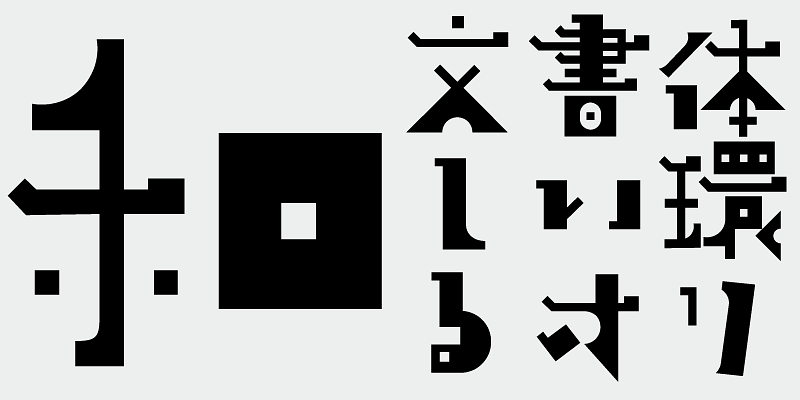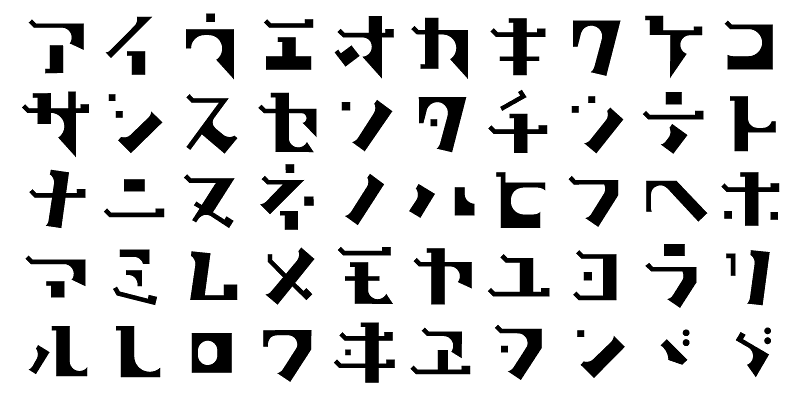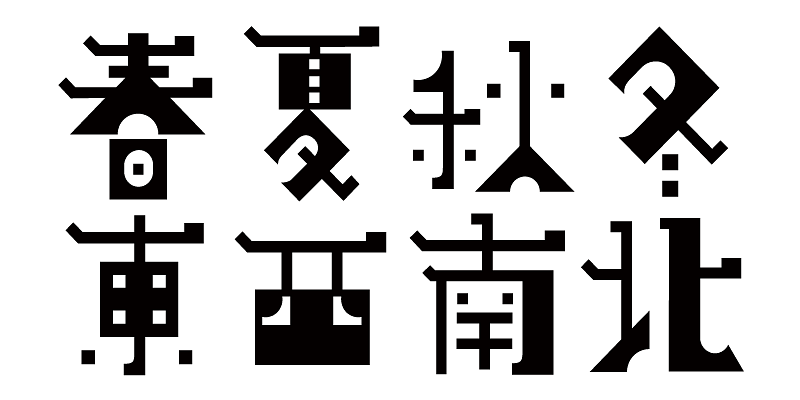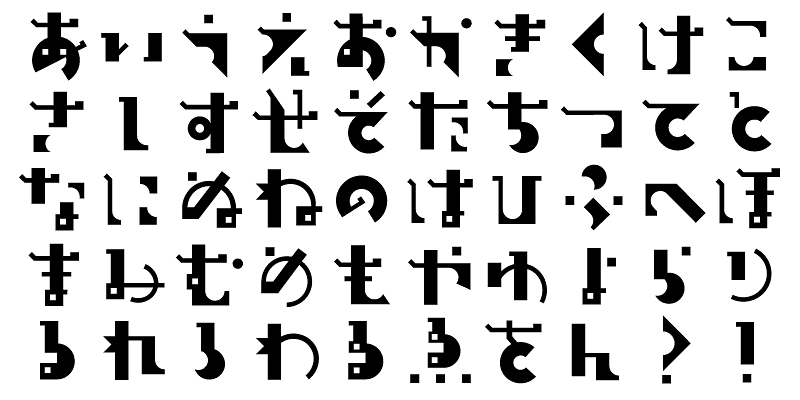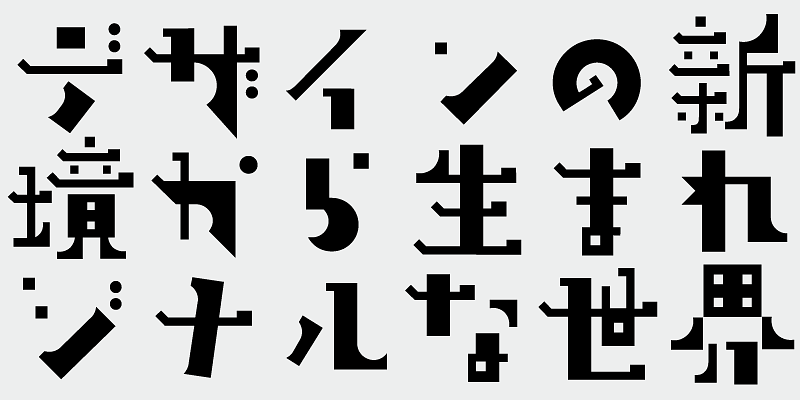
서체는 가독성도 중요하지만, 제 경우에는 제작 시 문자뿐만 아니라 그림과 기호로도 나타나 시각적으로도 즐거움을 주는 큰 도전을 했습니다. 이는 훗날 디자인된 AB-Shoutenmaru 서체의 큰형님뻘이 됩니다.
이 글꼴에는 신문사, 출판사, 언어 연구소가 만든 문자 빈도표에서 선정된 가장 많이 사용되는 간지 문자 1,000개와 더불어 206개의 가나 문자와 구두점이 포함되어 있습니다.
오늘날 일본어 글꼴 제작에서는 JIS 표준의 7,000자가 필수로 간주됩니다. 그러나 모든 글꼴에 정말 7,000자가 필요할까요? 사진 식자 시대에는 훨씬 적은 수의 문자가 필요했습니다. 독립 서체 디자이너 그룹인 FONT1000은 그 간단한 질문으로 시작했습니다. 일본어 서체에 필요한 최소 1,000자의 한자(표의 문자)를 선택했고 이를 지원하는 서체와 글꼴을 적극적으로 만들었습니다. 이 1,000자의 한자 문자 세트는 신문사, 출판사, 언어 연구 기관 등에서 수집한 문자 빈도 데이터를 사용하여 선택되었으며 가나 음절 문자 및 구두점도 포함합니다. FONT1000은 2001년에 25명의 디자이너와 25개의 서체로 시작했습니다. 현재는 130개의 서체를 보유 중이고 거의 40명의 멤버를 포함하도록 성장했으며, 더 많은 문자가 있는 글꼴 작업이 가능하게 되었습니다.